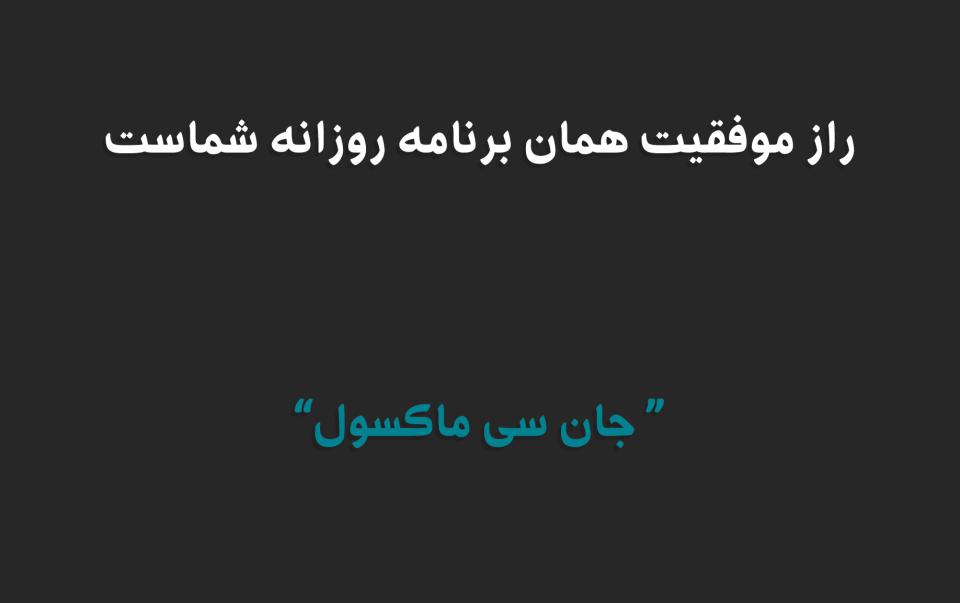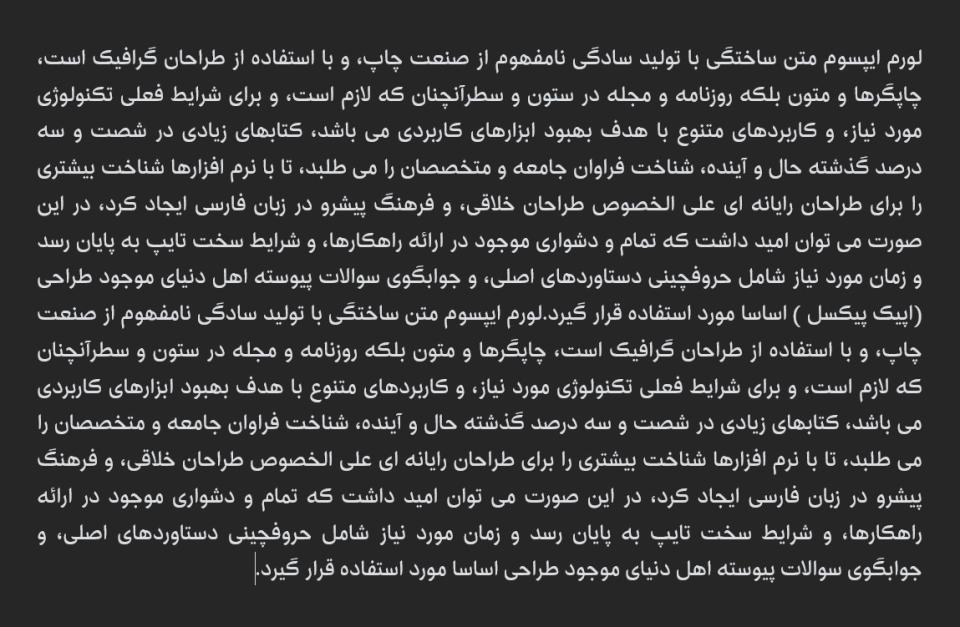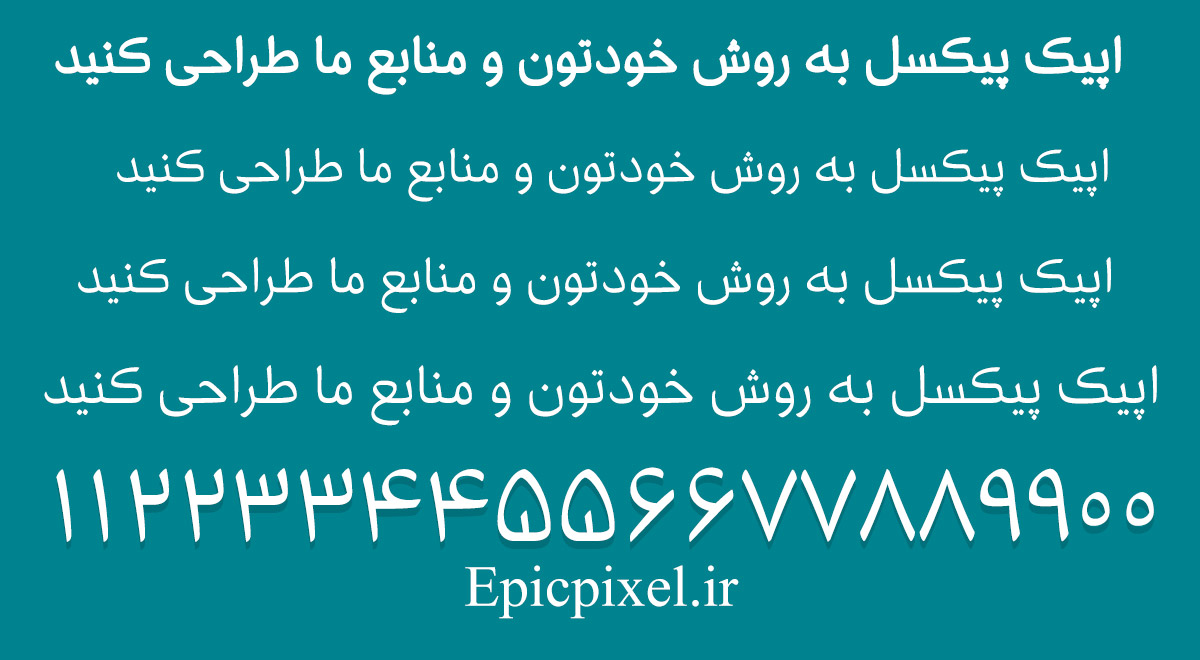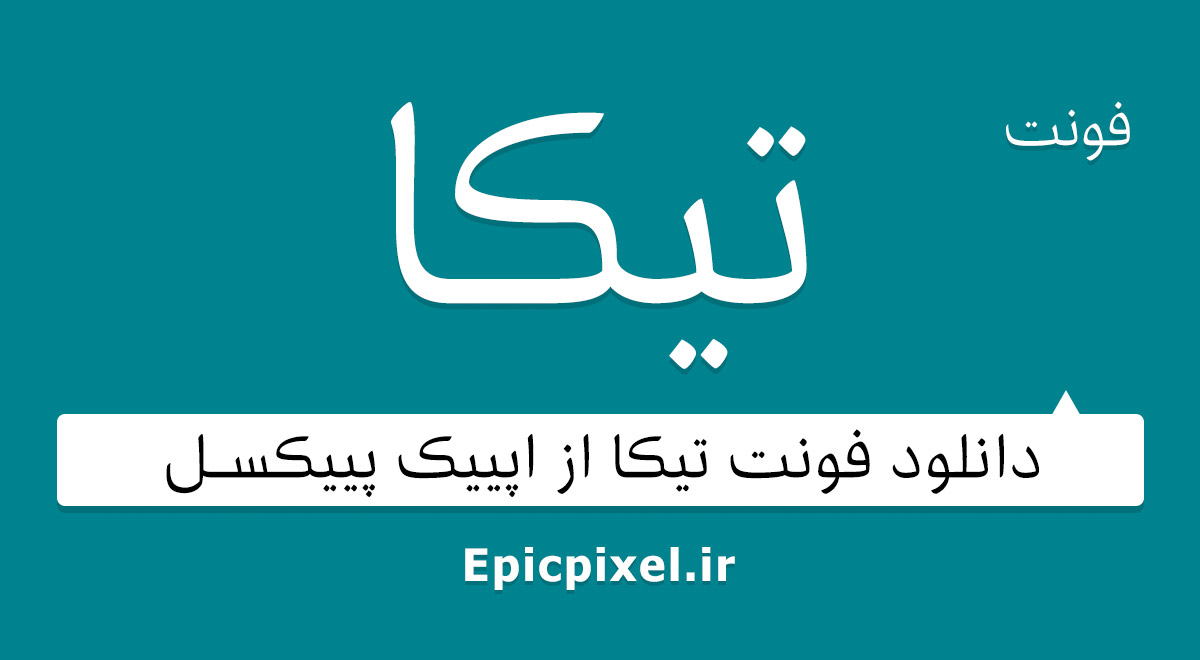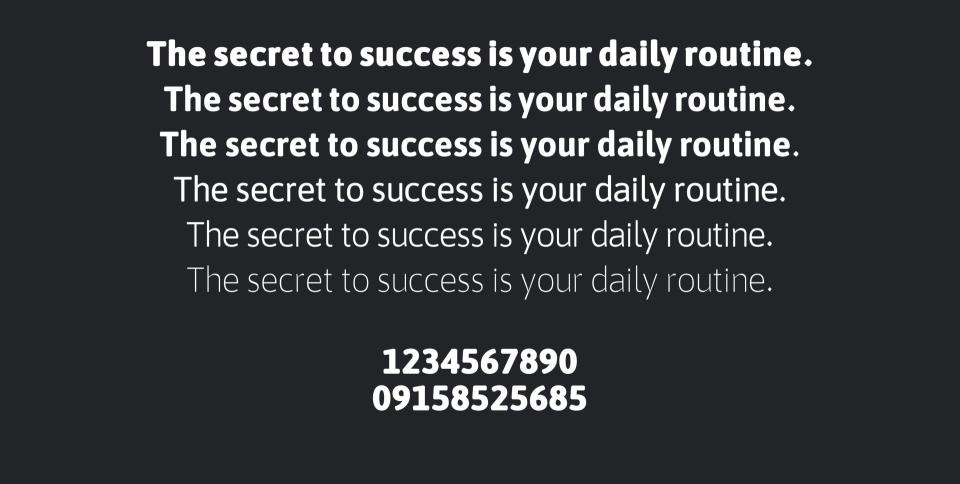
6 فونت تیکا فارسی
فونت تیکا فارسی به دلیل ویژگی های منحصربه فردش، انتخابی ایده آل برای طراحان و نویسندگانی است که به دنبال کیفیت و زیبایی در آثار خود هستند. این فونت با طراحی مدرن و خوانایی بالا، تجربه ای متفاوت از تایپ فارسی را ارائه می دهد.
یکی از ویژگی های برجسته تیکا، هماهنگی بی نظیر آن با زبان فارسی است؛ حروف به گونه ای طراحی شده اند که به روانی و زیبایی متن فارسی می افزایند. این فونت در اندازه های مختلف، چه در متن های طولانی و چه در عناوین کوتاه، خوانایی خود را حفظ می کند و چشم را خسته نمی کند. همچنین، تیکا از تنوع وزنی مناسبی برخوردار است که به شما امکان می دهد برای هر نوع محتوایی، وزن مناسب را انتخاب کنید.
در کنار مزایا، باید به این نکته هم اشاره کرد که به دلیل طراحی خاص تیکا، ممکن است در برخی موارد خاص، مانند استفاده در نرم افزارهای قدیمی یا سیستم عامل های خاص، نیاز به تنظیمات جزئی باشد. با این حال، این مسئله با به روزرسانی نرم افزارها به راحتی قابل حل است.
اگر به دنبال فونتی هستید که هم زیبایی بصری داشته باشد و هم خوانایی متن شما را بهبود ببخشد، تیکا گزینه ای عالی است. این فونت با طراحی حرفه ای و دقت در جزئیات، به نوشته های شما جلوه ای خاص می بخشد و تجربه کاربری بهتری را برای مخاطبان فراهم می کند. تیکا نه تنها یک فونت است، بلکه ابزاری قدرتمند برای خلق آثار بصری جذاب و متن های خواندنی است.